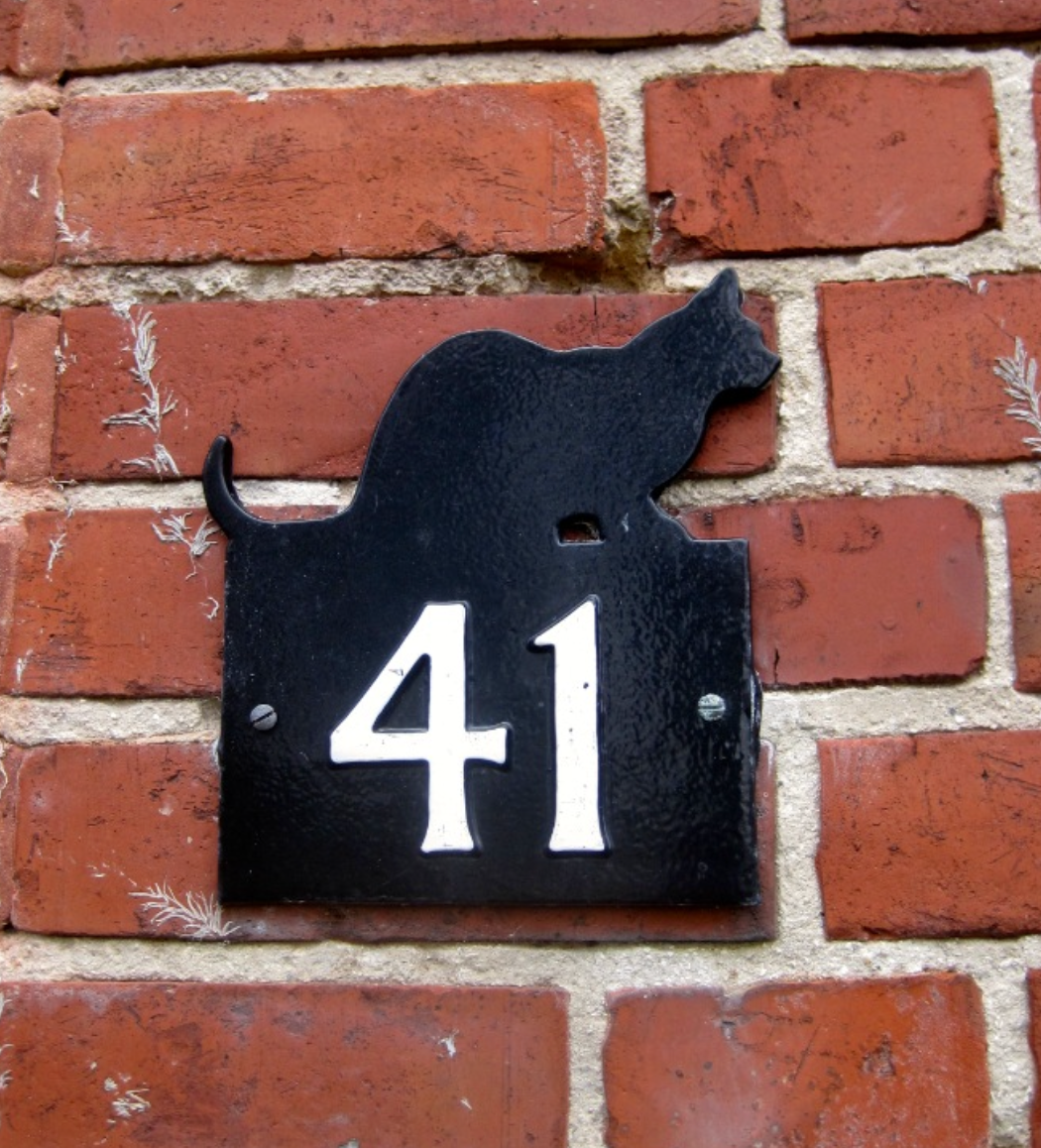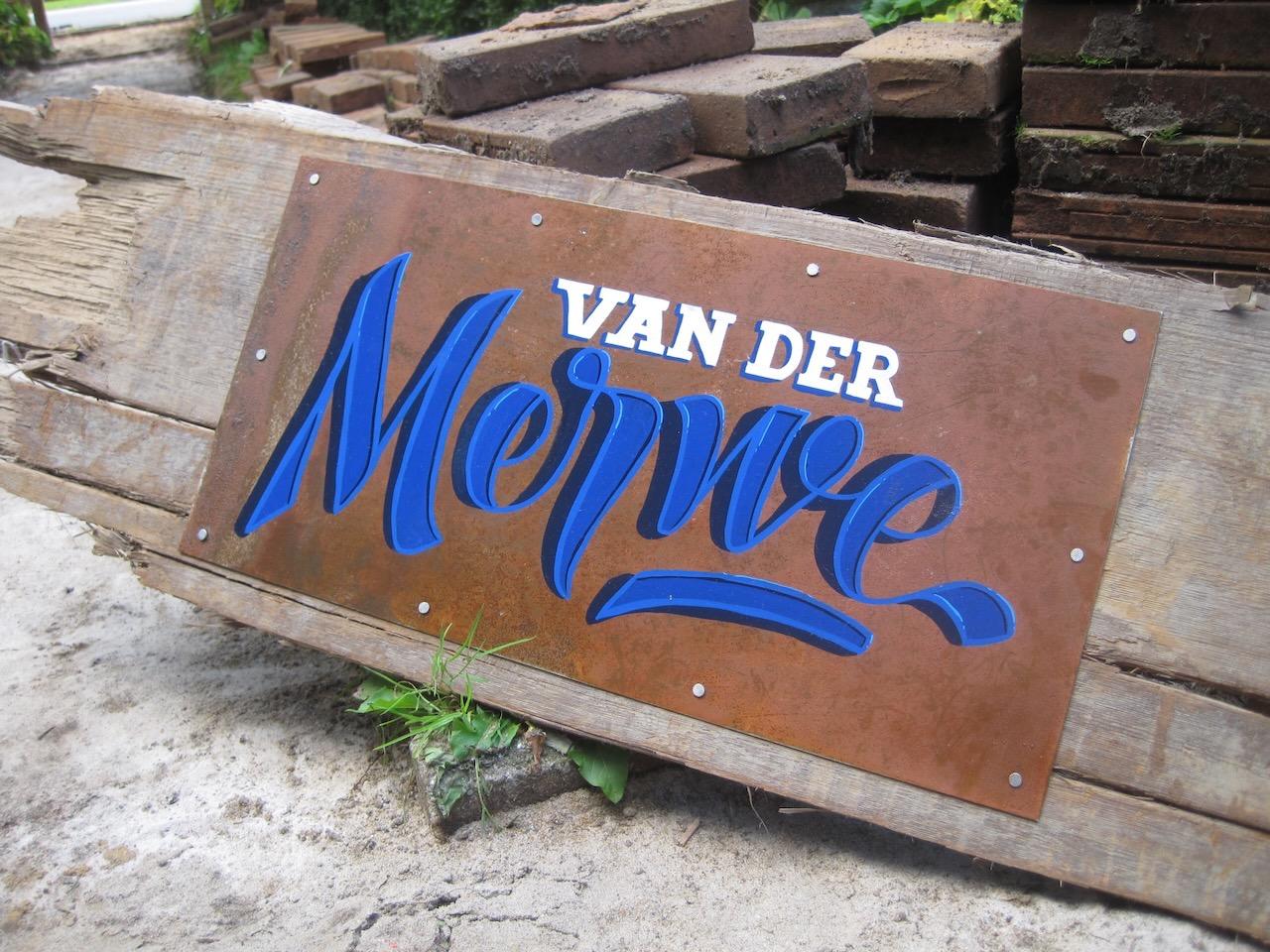
Hersteller für schöne Namens- und Hausnummernschilder in Emaille gesucht
kennt ein/r von Euch einen Hersteller schöner Emailleschilder für Hausnummer und Name an der Haustür? Die gängigen Hersteller, die die Suchmaschine ausspuckt, haben eine doch recht übersichtliche Auswahl von Schriften:
Ich würde sehr gerne eine Schrift verwenden, die zumindest annähernd in die Zwanzigerjahre des vergangenen Jahrhunderts passt. Das wäre – bei der schmalen gezeigten Auswahl – noch am ehesten die Times New Roman (Baujahr 1933). Nur wurde die ja nicht gerade für Emailleschilder entworfen – so richtig aufregend finde ich sie für diesen Zweck nicht, was sagt Ihr? Und kennt Ihr vielleicht Hersteller mit einer breiteren Schriftenauswahl?
Keine eigene Erfahrung, aber die Möglichkeiten – auch mit angeliefertem Design – dort scheinen schier unendlich …
Ach, da hatte ich ja wirklich ein Brett vorm Kopf – bei denen war ich nämlich auch schon auf der Seite, aber ich habe nur oben bei den Standardprodukten nachgeschaut und bin nicht drauf gekommen, dass die auch individuell fertigen können. Hätte ich mal bloß ein bisschen weiter nach unten gescrollt … :oops:
Mir scheint das Angebot der meisten Anbieter, die die Suchmaschine ad hoc ausspuckt, recht ähnlich zu sein. Sehr gut möglich, dass die alle auf den gleichen externen Emaillemeister zurückgreifen. Aber sofern ich dort eine schöne Hausnummer und ein kleines feines Klingelschild für meinen offiziellen Hauseingang bekomme, ist das in Ordnung für mich. :-D
Eine kleine Hausnummer gab’s übrigens schon am Haus, als ich einzog (die bleibt auch dran):
OT: Für den privaten Freunde-Eingang habe ich ja schon lange ein ganz wunderbares, handgefertigtes Meisterschildermalerschild, welches ich vor ein paar Jahren zum Einzug von zwei überaus geschätzten Forumskollegen verehrt bekommen habe. :biglove:
handgefertigtes Meisterschildermalerschild
Also eine Meisterarbeit ist das nicht gerade, wenn ich mir das so genau angucke – besonders das D und A … :roll::aschehaupt:
Aber das ist schnuckelig:
Ich liebe das Schild mit all seinen Ecken und Kanten. Es ist durch so viel Freundschaft entstanden – es könnte gar nicht schöner sein. :biglove: